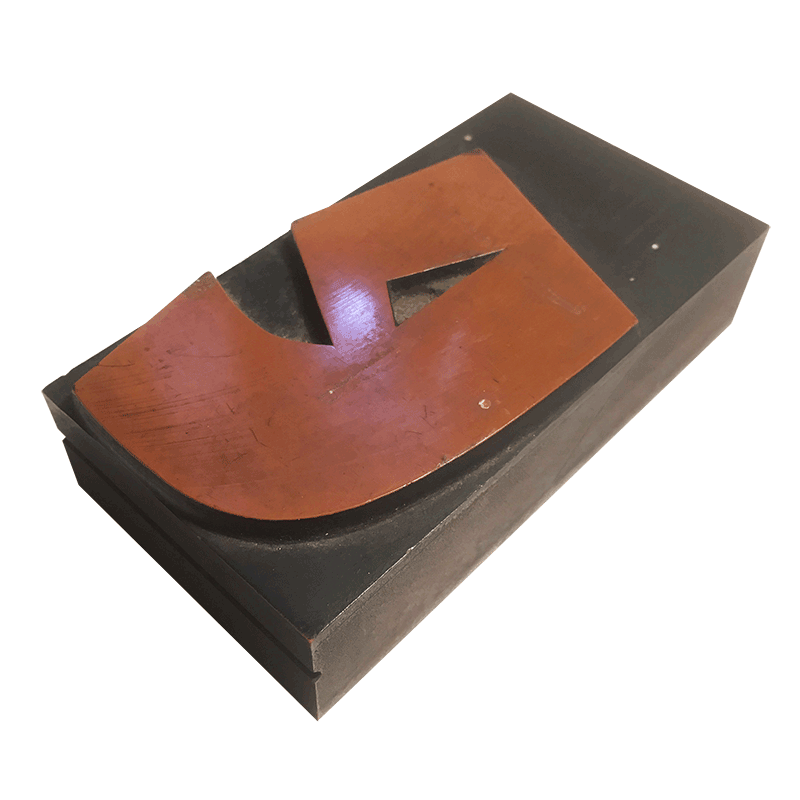
Ein Begriff aus dem Polnischen, der in abwertender Weise für einen Tölpel oder ungehobelten Burschen verwendet wird. In Druckereien wurde der Begriff für Setzergehilfen bzw. ungeschickte Setzer verwendet, mitunter aber auch im weiteren Sinne für alle Setzergesellen ohne Meisterbrief.
Die Paginierung sind die Seitenzahlen einer Publikation. Bei Büchern beginnt die Paginierung in der Regel auf der Schmutztitelseite, wobei besonders bei Fachbüchern häufig erst ab dem ersten Kapitel arabisch und zuvor römisch nummeriert wird. Bei Magazinen wird häufig auch schon das Cover als Seite eins gezählt. Die Umschlagseiten werden auch mit U1 bis U4 bezeichnet (allerdings nicht so nummeriert).
PFB steht für PostScript Font Binary und ist der Suffix einer Datei die zu einem Postscript-Type1-Font gehört. Die PFB-Datei enhält die Outline-Daten eines Fonts. Windows benötigt neben der PFB-Datei auch eine PFM-Datei um installiert und benutzt werden zu können.
PFM steht für PostScript Font Metrics und ist der Suffix einer Datei die zu einem Postscript-Type1-Font gehört. Die PFM-Datei enhält Metrikdaten wie zum Beispiel Unterschneidungswerte. Windows benötigt neben der PFM-Datei auch eine PFB-Datei um installiert und benutzt werden zu können.
PFR steht für Portable Font Resource und ist der Suffix einer Fontdatei, die zur Verwendung mit der Schrifteinbettungstechnolgie TrueDoc benutzt wurde.
Photofonts sind Bitmapfonts, die Farben und Transparenzen unterstützen. Die einzelnen Glyphen bestehen dazu aus PNG-Bildern. Das Format wurde von Fontlab Ltd. entwickelt, wird aber kaum von Anwendungsprogrammen unterstützt. Siehe auch http://www.photofont.com
Plakadur war ein Markenname der H. Berthold AG für ein auf Kunstharz basierendes Material, das im 20. Jahrhundert zur Produktion von großformatigen Buchdruck-Schriften als Alternative zu Holzschriften eingesetzt wurde. Im Vergleich zu letzteren ist das Plakadur-Material formstabiler, da es nicht nicht auf Feuchtigkeit, Lösungsmittel etc. reagiert. Als Rohstoff zur Fertigung dient ein Edelkunstharzprodukt in Streifenform von ungefähr Kegelstärke und Schrifthöhe. Die Kegelseiten werden auf e
Polytype (Plural: Polytypen) war eine alternative Bezeichnung von Logotype.
PostScript Type 0 ist eine Erweiterung von PostScript Type 1, das in Gegensatz zu letzterem eine Adressierung von mehr als 256 Zeichen ermöglicht. Es wurde vor allem für asiatische Fonts mit großem Zeichenvorrat benutzt. Das Format ist vor allem unter der Abkürzung CID (Character Identifier Font) bekannt.
Adobe veröffentlichte 1985 den PostScript-Standard, eine Seitenbeschreibungssprache zur größenvariablen Druckausgabe von Dokumenten, und mit dem im gleichen Jahr erschienenen, auf PostScript basierenden Apple LaserWriter begann die Revolution des Desktop Publishing – dem Publizieren vom Schreibtisch aus. Innerhalb des PostScript-Standards etablierten sich zunächst zwei wesentliche Schriftformate: Type-1- und Type-3-Fonts. Für Letztere waren die Spezifikationen frei zugänglich. Allerdings war di
Private Use Area (»Private Verwendung«) ist ein Bereich im Unicode-Standard, für den keine festen Zeichen zugeordnet sind. In der Basic Multilingual Plane erstreckt sich der PUA-Bereich von U+E000 bis U+F8FF. Schrifthersteller können diesen Bereich nutzen, um Zeichen, für die kein eigener Unicode-Wert existiert, zu kodieren. Typisch sind hier etwa Kapitälchen, Schwungbuchstaben und Ornamente aller Art. Apple nutzt zum Beispiel den Kode U+F8FF für das Apple-Logo. Da die Private Use Area nicht sta
Proportionale Ziffern besitzen im Gegensatz zu Tabellensatzziffern eine unterschiedliche Dickte der einzelnen Ziffern.
Abkürzung von Private Use Area
Punze (von lateinisch »punctio«: Stechen) oder auch Bunze (veraltet) hat zwei Bedeutungen: Die Punze ist ein Werkzeug bei der Erstellung von Bleisatz-Stempeln. Damit müssen die Innenformen von Buchstabenvorlagen (Abbildung: fig 2) nicht manuell graviert werden, sondern werden durch das Einschlagen mit der Punze (Abbildung: fig 1) erzeugt. Die durch das oben genannte Werkzeug erstellten, nicht druckenden Innenformen eines Buchstabens bzw. des gedruckten Buchstabenbildes werden ebenf
Die vier Umschlagseiten werden mit U1 bis U4 bezeichnet. Das erste, was man von einer Publikation, sei es nun Buch, Zeitschrift oder sonst etwas, sieht, ist die Seite U1. Schlägt man das Werk auf, schaut man links auf die, bei Büchern in der Regel unbedruckte, Seite U2 (und bei Büchern rechts dann auf den Schmutztitel). Blättert man nun das ganze Werk durch, bis man die letzte Seite umgeschlagen hat, dann ist links die letzte Seite des Werkes und rechts liegt U3, bei Büchern meistens ebenf